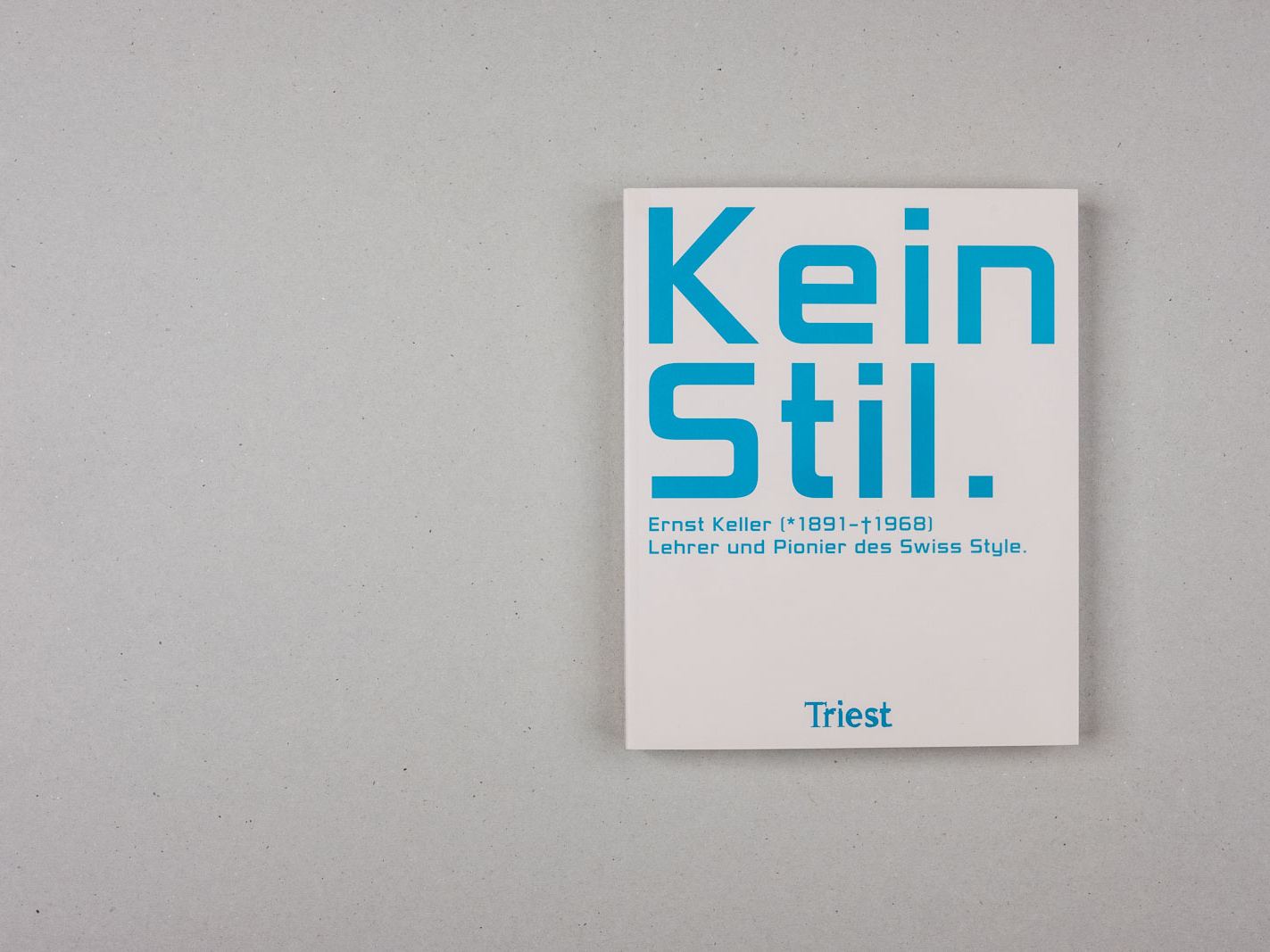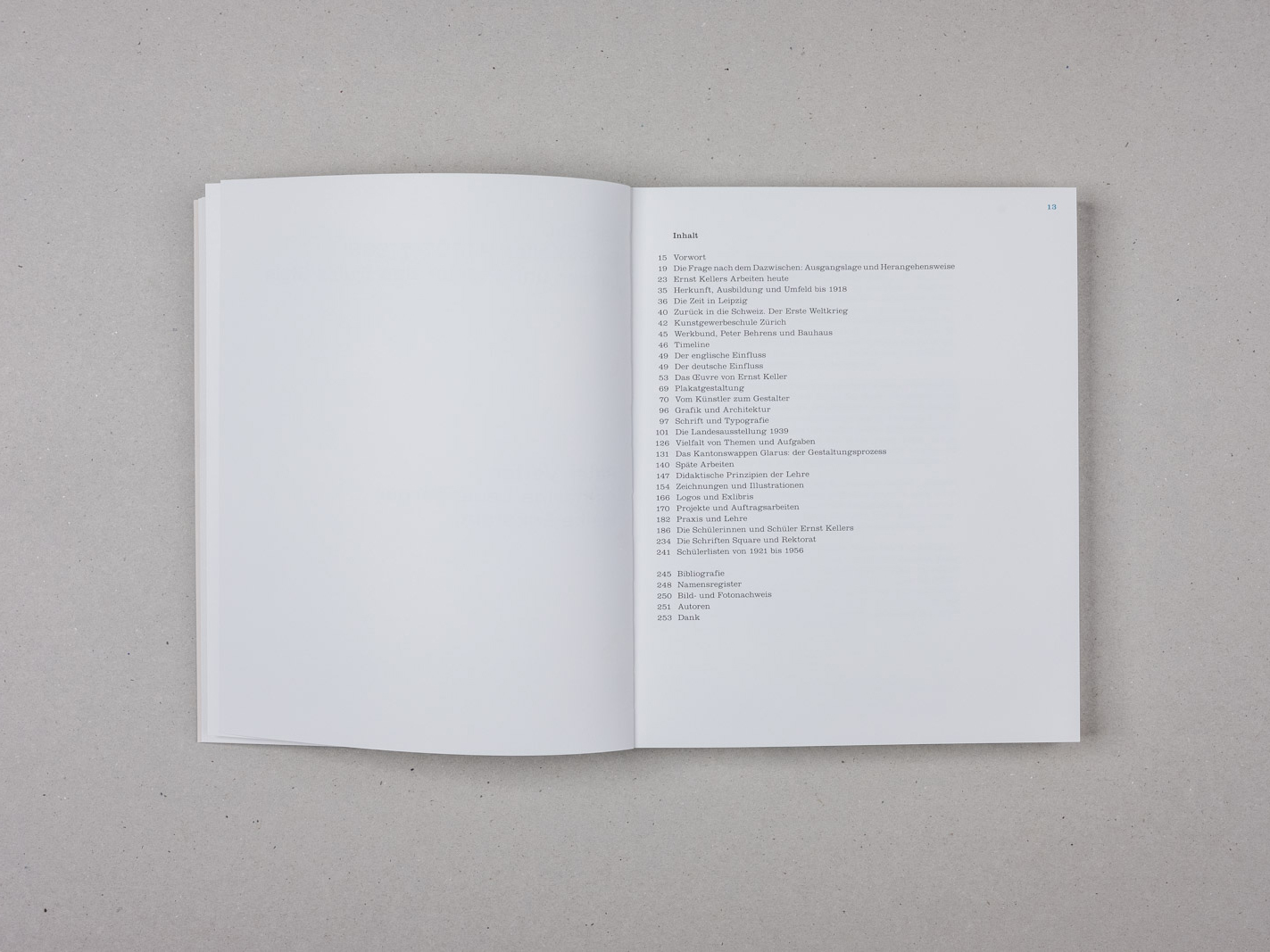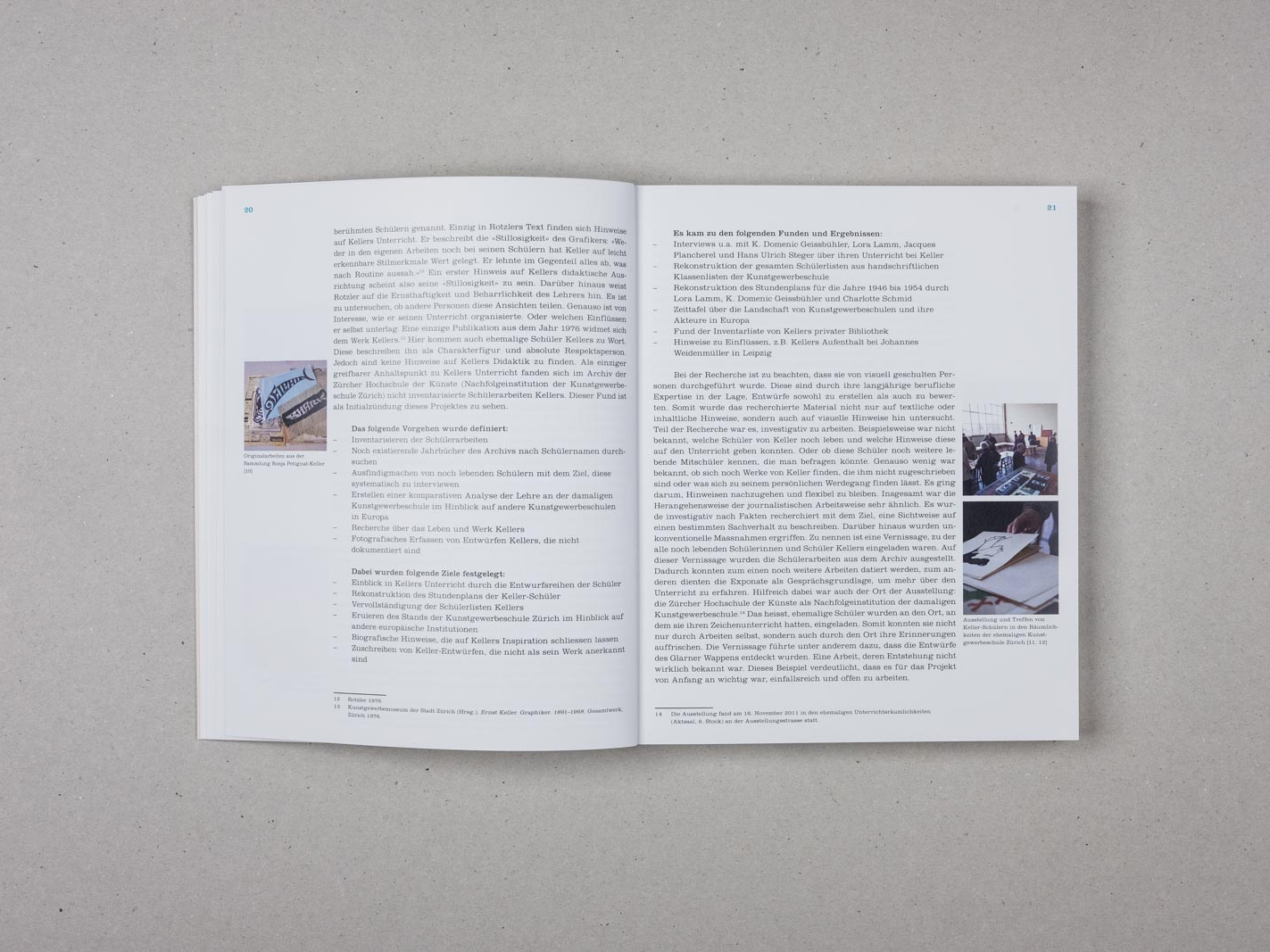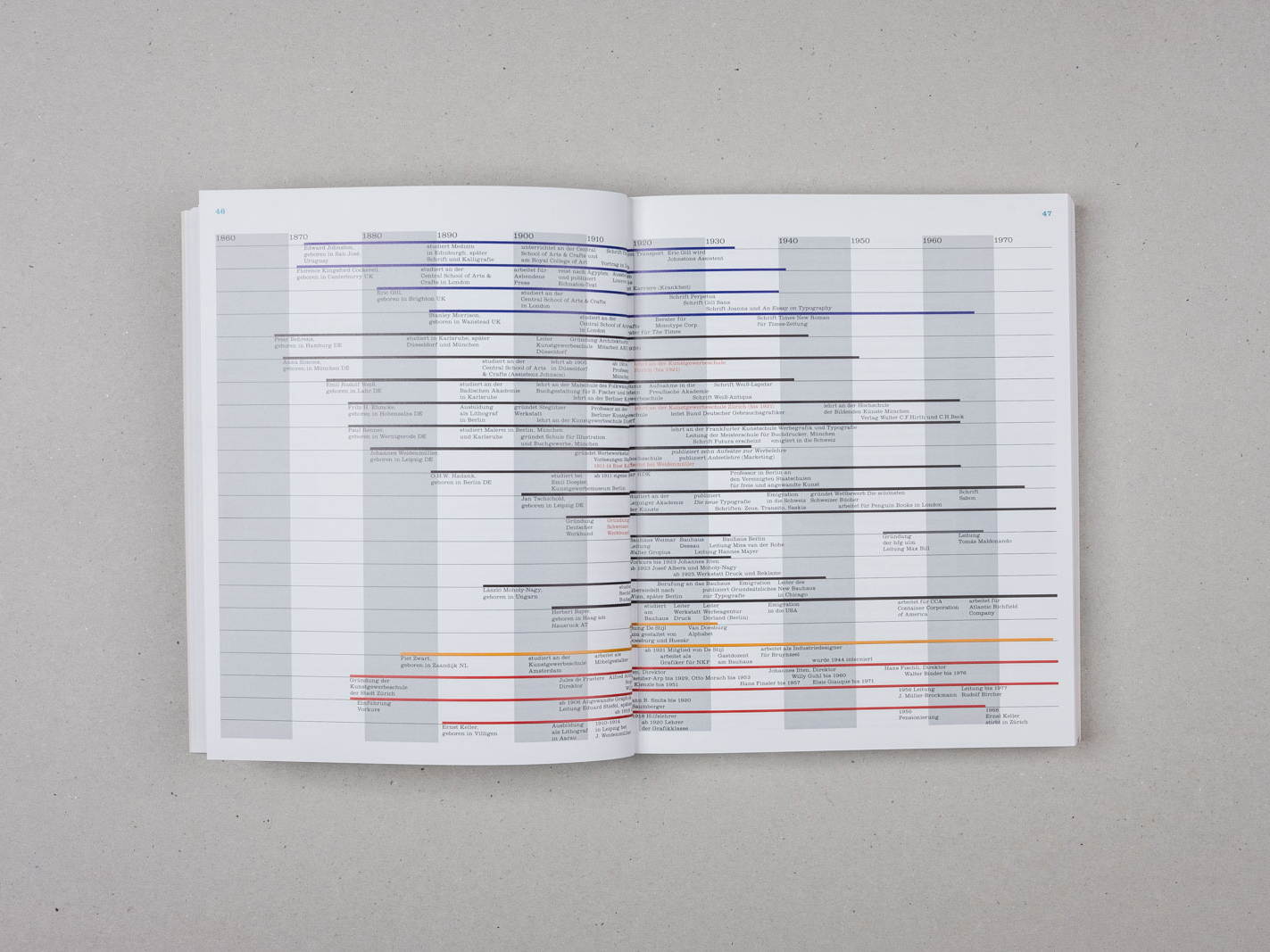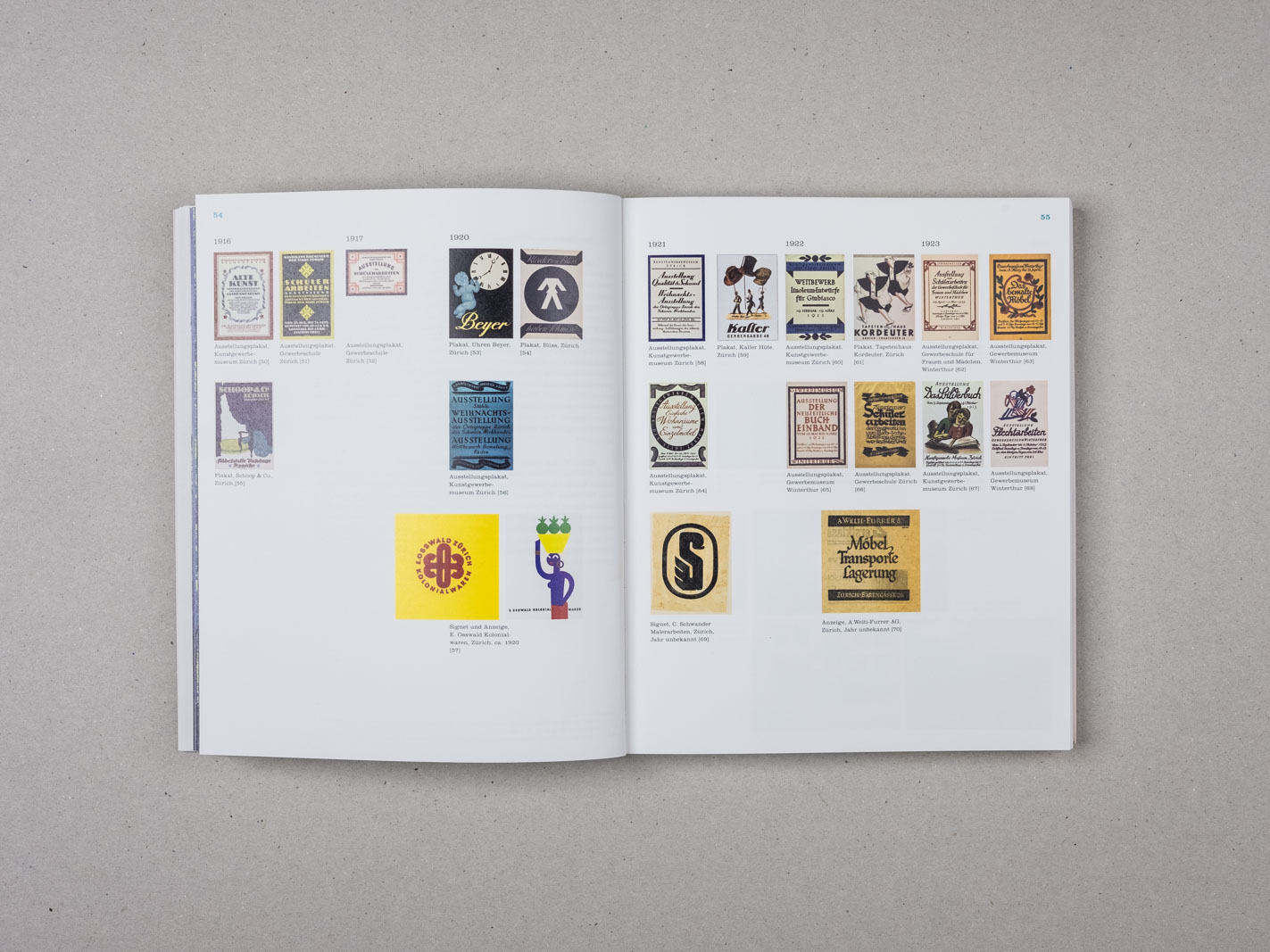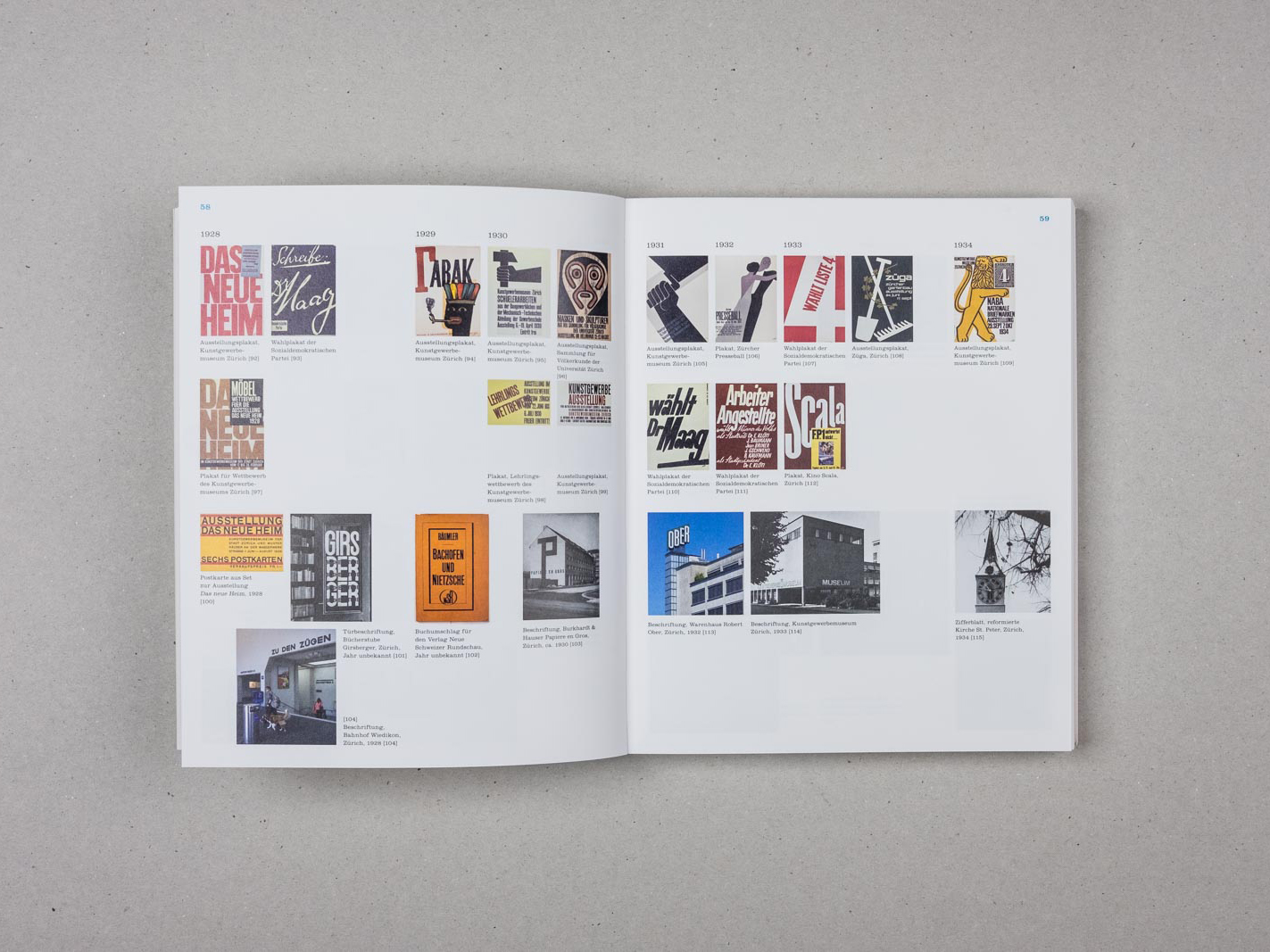
Peter Vetter, Katharina Leuenberger, Meike Eckstein
Kein Stil. Ernst Keller (1891–1968)
– Lehrer und Pionier des Swiss Style
Buchgestaltung: Coande, Männedorf
→ erste umfassende Monografie zu Ernst Keller
Verschiedentlich und insbesondere in den USA wird in der Geschichtsschreibung des Grafikdesigns auf Ernst Keller als Vater des sogenannten Swiss Style, später International Typographic Style, hingewiesen. Diese Tatsache gründet auf der grossen Anzahl von Keller-Schülern, die später diesen Swiss Style geprägt und berühmt gemacht haben. Die Leistung von Keller wird einzig durch sein Œuvre, vor allem seine Plakatgestaltung oder seine Beschäftigung im Zusammenhang mit Schrift- und Grafik in der Architektur, gewürdigt.
Fundamental jedoch ist Ernst Kellers Beitrag zur Entwicklung von innovativen, nicht akademischen didaktischen Prinzipien in der Gestaltungsausbildung. Seine Lehrtätigkeit ab 1918 kann als eines der weltweit ersten systematischen Ausbildungsprogramme für Grafikdesign definiert werden.
Aus der intensiven Lehrtätigkeit von 1918 bis 1956 sind sehr unterschiedliche Gestalterinnen und Gestalter hervorgegangen. Es sind dies die Protagonisten der neuen Grafik wie Richard Paul Lohse, Josef Müller-Brockmann und Carlo Vivarelli oder verschiedenste illustrativ-künstlerische Talente wie Heiri Steiner, Lora Lamm oder K. Domenic Geissbühler und innovative Gestalter wie Hermann Eidenbenz oder Gérard Miedinger. Wissenschaftliche Illustratoren wie H.P. Weber oder der Karikaturist H.U. Steger. Einen anderen Schwerpunkt bilden Gestalter mit internationaler Lehrtätigkeit wie Pierre Gauchat, Walter Käch, Robert Sessler, Fred Troller, Josef Müller-Brockmann und andere.
Diese Vielfalt der Talente dokumentiert eindrucksvoll die Offenheit, Nachhaltigkeit und jede Dogmatik negierende Lehrtätigkeit von Ernst Keller.